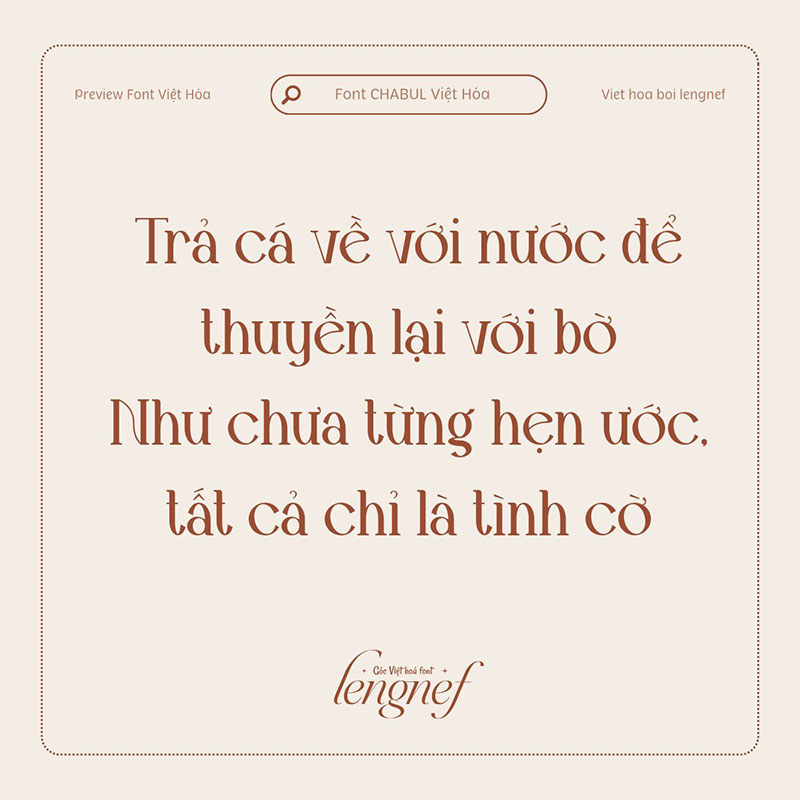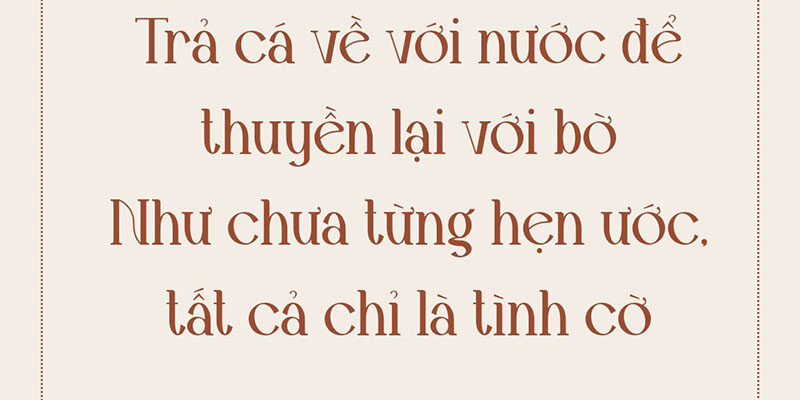
Việt hóa theo yêu cầu 08 || LF Chabul
- Tác giả: Maiko Hatta
Chabul – Phông chữ hiện đại là một phông chữ hiển thị mạnh mẽ và chân thực. Phông chữ này phù hợp cho bất kỳ dự án xây dựng thương hiệu nào như thiết kế logo, mẫu thiết kế và nhiều hơn nữa.